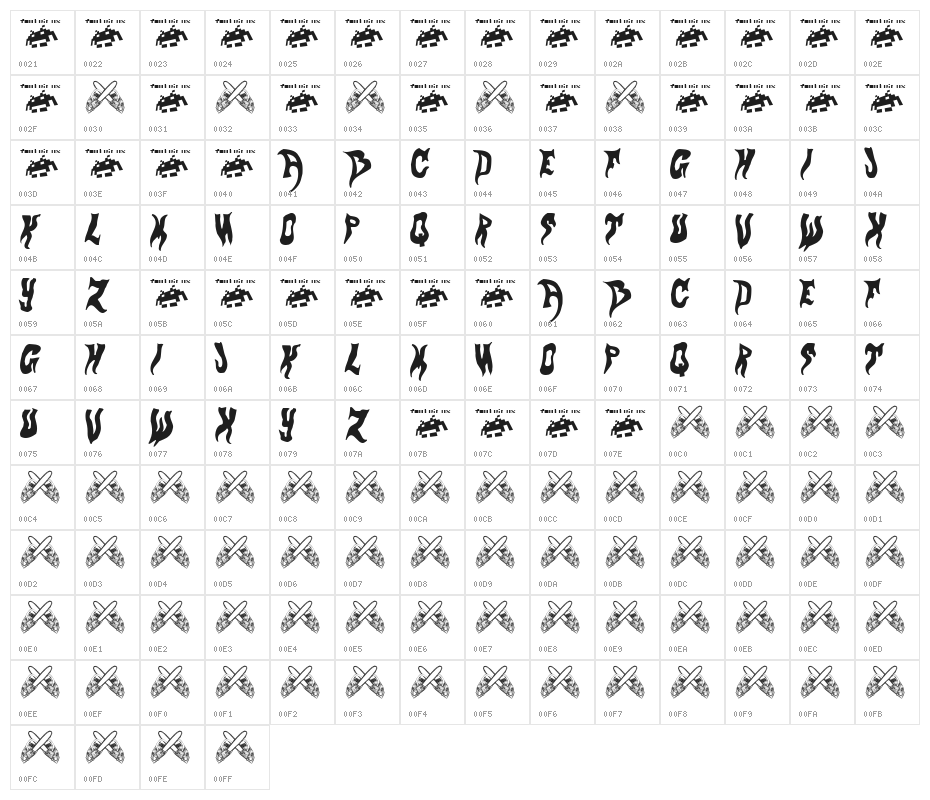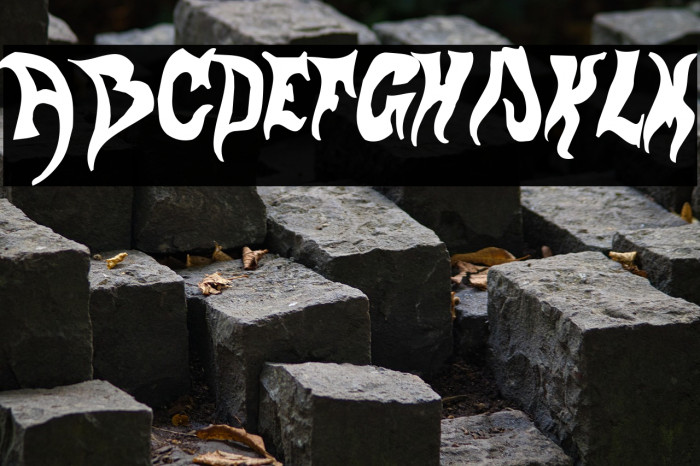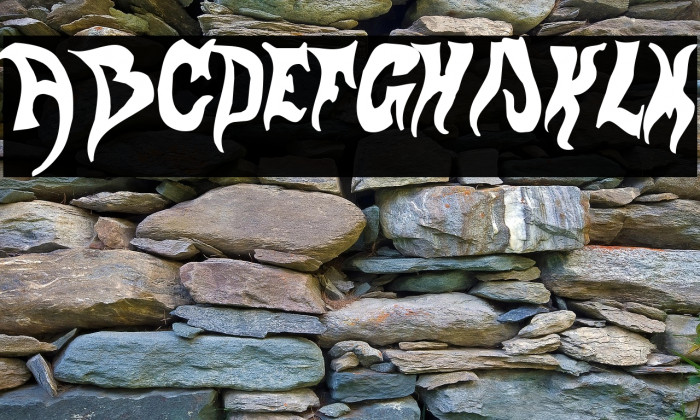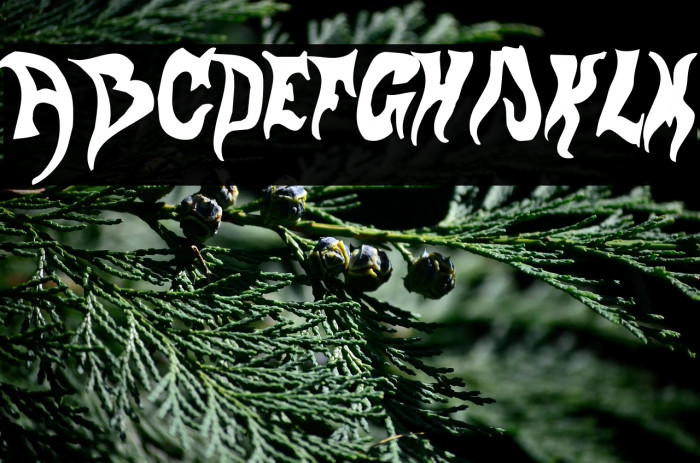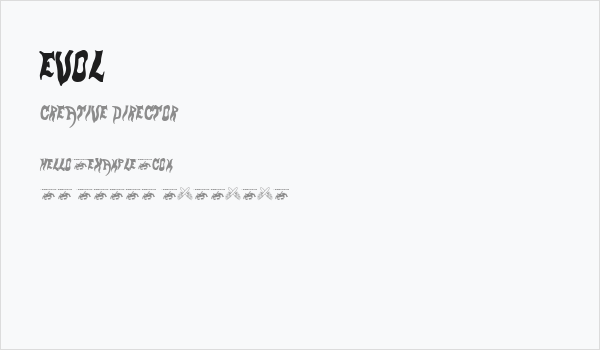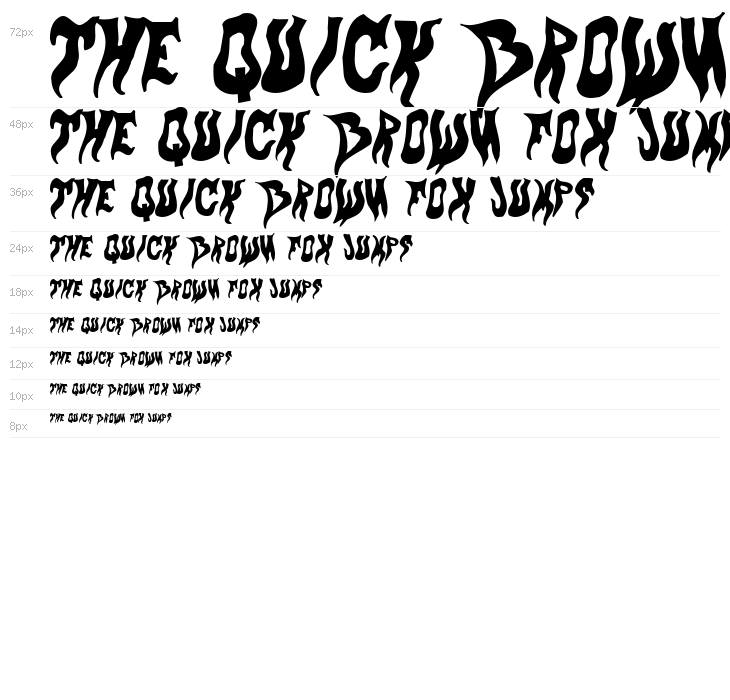
evol Font
| Progetti proposti | Perfect for music album covers, video game titles, extreme sports branding, or any project needing a bold, intense aesthetic. |